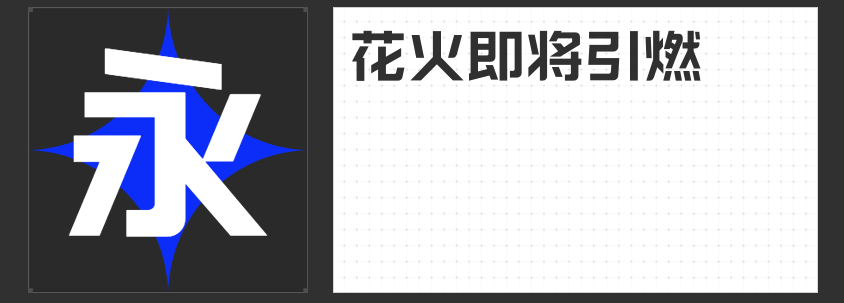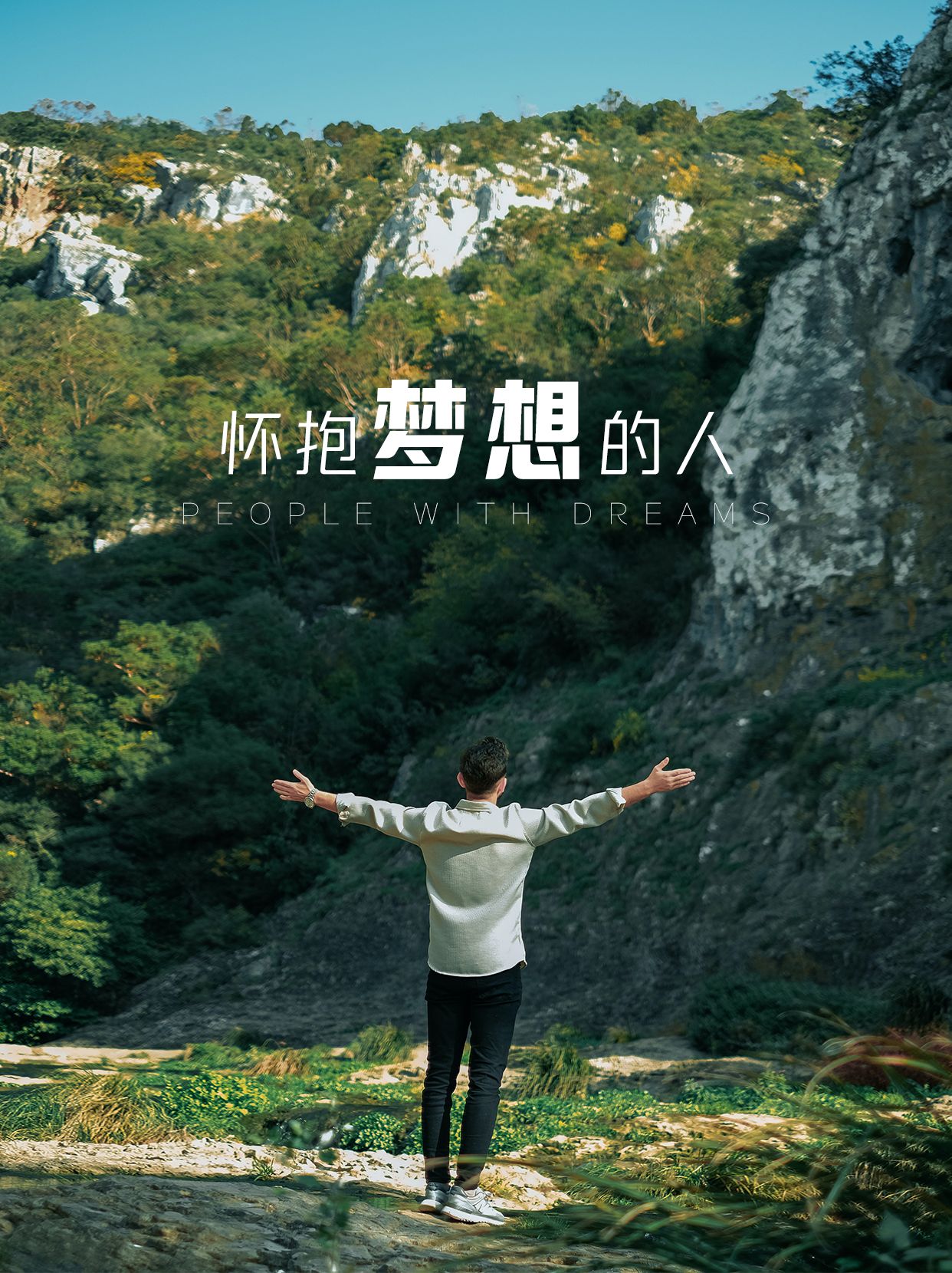
品牌设计必备:四款卓越字体推荐
在品牌设计中,字体选择至关重要,它不仅影响视觉美感,还关乎信息传递和品牌形象的塑造。今天,我们为您推荐四款专为品牌设计而生的卓越字体,它们各具特色,能够满足不同风格与需求的排版要求。
高手庆科智雅体 大黑以其直线设计、中宫略大、布白均匀的特点脱颖而出。这款字体笔画多变灵活,以连笔折笔为特色,整体做切口处理,优化尖锐部分,视觉秩序感强烈。其西文符号与中文风格统一,为品牌设计提供了丰富的视觉层次和阅读体验。无论是现代简约还是复古风格,都能轻松适配。
励字钧线黑简 微黑以其完美的斜度和利索的转折著称,用棱角改变世界的圆滑。这款字体摒弃过度装饰,加强细节优化,降低阅读障碍,为读者带来舒适体验。全直线的设计符合当代视觉审美,使字体成为画面主角,独树一帜。它适用于各种品牌宣传材料,能够彰显品牌的独特个性和现代感。
励字勇敢黑简 大黑以其粗壮有力的笔画和易于阅读的特性受到青睐。没有衬线装饰,撇捺等笔画不尖,横直均匀,突出醒目。这款字体常用于标题、导语和标志等,能够迅速吸引观众注意力,传递品牌的核心价值。
四、励字造梦简 中粗
励字造梦简 中粗的设计灵感来源于“青春筑梦”,其不对称设计和夸张的透视感模拟了建筑的宏壮。这款直线型字体有力量感,棱角分明,字形轮廓清晰有力。它不仅能够提升品牌形象的独特性,还能激发观众的想象力和创造力。
这四款字体各具特色,能够满足品牌设计在不同场景下的需求。选择适合的字体,让您的品牌形象更加鲜明、独特,助力品牌走向成功。